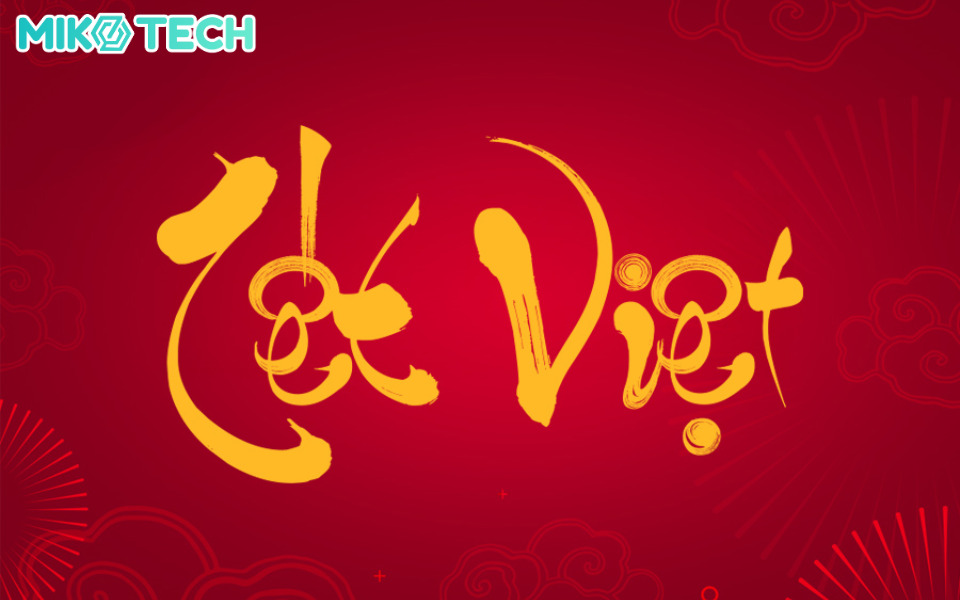
15+ Font Chữ Tết Chúc Mừng Năm Mới Ấn Tượng Và Độc Đáo
Chọn font chữ Tết phù hợp không chỉ giúp bạn tạo điểm nhấn mà còn mang lại cảm giác ấm áp, vui tươi cho các thiết kế dịp năm mới. Hiện nay, có rất nhiều font Tết đẹp với nhiều phong cách khác nhau từ thư pháp cổ điển cho đến hiện đại. Trong bài viết này, Miko Tech sẽ chia sẻ bộ sưu tập font chữ Tết đẹp mắt, giúp bạn thổi hồn xuân vào mỗi thiết kế.
Font chữ Tết là gì?
Font chữ Tết là các kiểu chữ được thiết kế để phù hợp với không khí và tinh thần của Tết Nguyên Đán, mang đậm phong cách lễ hội truyền thống của người Việt Nam.
Font chữ Tết đẹp
Font chữ đẹp sẽ giúp nâng tầm thiết kế của bạn
Font chữ Tết mang đậm dấu ấn văn hóa Phương Đông gợi nhớ về những hình ảnh quen thuộc trong mùa Tết. Các font Tết thường được lấy cảm hứng từ thư pháp hoặc nét viết tay mềm mại, uyển chuyển. Những font chữ Tết được sử dụng trong các thiết kế liên quan đến Tết như bao lì xì, thiệp chúc mừng, banner, poster, hoặc các sản phẩm trang trí vào dịp Tết.
Tổng hợp 15+ font chữ Tết đẹp trong thiết kế
Khi thiết kế với chủ đề Tết, việc chọn font chữ phù hợp là một thử thách thú vị. Làm sao để tìm được font chữ Tết không chỉ mang đậm nét văn hóa truyền thống mà còn thể hiện được màu sắc riêng của nhà thiết kế hoặc thương hiệu? Cùng xem qua những font chữ chúc mừng năm mới đẹp, độc đáo ngay sau đây!
1. Font chữ Tết TH Culture
TH Culture là một font Tết đẹp cho những thiết kế năm mới mang đậm phong cách trẻ trung nhưng vẫn dễ nhìn. Với kiểu chữ to bản kết hợp những đường nét uốn lượn mềm mại, TH Culture không chỉ mang vẻ đẹp hoài cổ mà còn tỏa lên sự thanh lịch và tinh tế. TH Culture sẽ là font chữ lý tưởng để sử dụng làm font chữ chúc mừng năm mới cho các thiết kế bao bì, social post, banner của các thương hiệu bánh ngọt hoặc hoạt động trong lĩnh vực F&B.
Font chu TH Culture xua hoai co
Font chữ tết đẹp TH Culture xưa hoài cổ
2. Font Thư Pháp Đức Thủy
Thư Pháp Đức Thủy là một font chữ tết thư pháp vô cùng ấn tượng và độc đáo. Với các nét chữ sắc sảo, vừa cứng rắn vừa uyển chuyển, Thư Pháp Đức Thủy là một font chữ Tết đậm đà bản sắc dân tộc và mang đậm tinh thần lễ hội. Ngoài ra, với khả năng hiển thị tốt trên nhiều chất liệu, font chữ Tết này rất hoàn hảo với các banner in câu đối, phong bì lì xì hay thậm chí cho các quảng cáo game kiếm hiệp sự kiện Tết nguyên đán.
Font Chữ Tết Thư Pháp Đức Thủy
Font chữ Tết Thư Pháp Đức Thủy
3. Font Tết Thư Pháp Đại Tự
Thư Pháp Đại Tự là một font chữ Tết thư pháp tuyệt vời cho những thiết kế mang đậm bản sắc văn hóa truyền thống Việt Nam. Các ký tự được dựa theo chữ viết thư pháp và nét bút đậm nhạt như khắc họa được lực tay của người cầm bút. Font Thư pháp Đại Tự có thể được sử dụng trong các sản phẩm như thiệp chúc Tết, câu đối, bao bì, hay các ấn phẩm đặc biệt trong Tết, mang đến sự trang trọng và đậm đà bản sắc dân tộc.
Font chu Tet dep Thu Phap Dai Tu 1
Font chữ Tết thư pháp Đại Tự
4. Font Tết Fantomen Việt hóa
Font Fantomen Việt hóa là một font chữ Tết đầy hoài cổ, gợi nhớ đến những nét đẹp xưa cũ của đất nước giai đoạn sau Giải phóng miền Nam. Lấy cảm hứng từ những bảng hiệu cũ trên đường phố ngày xưa, font chữ gốc của tác giả Bartek Nowak đã được Việt hóa để tái hiện nguyên vẹn giá trị văn hóa Việt Nam. Ngày nay, font chữ Fantomen Việt hóa có thể được dùng để thiết kế biển hiệu, bìa sách, bìa tạp chí, ấn phẩm truyền thông hoặc bao bì sản phẩm.
Font chữ tết Fantomen Việt hóa
Font Tết Fantomen Việt hóa cổ điển
5. Font chữ Christmas Carol
Christmas Carol là font chữ giáng sinh có nét chữ mềm mại, uốn lượn nhẹ nhàng và mang phong cách thư thái, lãng mạn. Khi được Việt hóa, font chữ này được sử dụng nhiều trong các ấn phẩm dịp lễ, kể cả dịp Tết, banner quảng cáo hoặc card cám ơn khi đóng gói sản phẩm.
font chữ christmas carol
Font chữ Christmas Carol có thể dùng được cho nhiều dịp lễ
6. Font chữ Tết Medino
Medino Serif là một kiểu chữ hiện đại với các đường nét gọn gàng, đường cong ấn tượng và mang đến một cảm giác sang trọng và đẳng cấp. Mặc dù được thiết kế để phù hợp cho tiêu đề, logo và bao bì sản phẩm nhưng Medino Serif hoàn toàn có thể trở thành lựa chọn tuyệt vời cho các thiết kế dịp Tết.
Medino Serif với các nét đầu, nét đuôi sang chảnh sẽ giúp chữ viết được đẹp mắt hơn nhưng vẫn đảm bảo mức độ dễ đọc. Font chữ Tết này có thể kết hợp tốt với các thiết kế tối giản và sang trọng, giúp nhãn hiệu và bao bì sản phẩm có vẻ đẹp tinh tế và độc đáo.
Font chu chuc mung nam moi Medino 1 1
Font chữ chúc mừng năm mới Medino
7. Font chữ cho Tết Sverige Script
Sverige Script là một kiểu chữ thanh thoát và điệu đà, mang lại vẻ đẹp mềm mại và uyển chuyển cho mọi thiết kế. Font chữ Tết Sverige Script có đường nét mảnh, đầy lãng mạn và hoàn hảo cho những dự án thiết kế dịp Tết. Hiện nay, font Tết đẹp Sverige Script đã được Việt hóa, do đó bạn có thể tải xuống để làm nổi bật các thông điệp xuân.
Font tet dep Sverige Script 1
Font Tết đẹp Sverige Script
8. Font Tết Classique Saigon Typeface
Font Classique Saigon Typeface là font chữ chúc mừng năm mới mang đậm dấu ấn hoài cổ được sáng tạo bởi tác giả Mạnh Nguyễn. Lấy cảm hứng từ những bảng hiệu cũ ở Sài Gòn giai đoạn Pháp thuộc, tác giả đã sáng tạo nên font chữ ấn tượng và phù hợp với những ấn phẩm hoặc thiết kế theo phong cách retro.
Xem thêm: 17+ Font Chữ Có Chân Đẹp Mắt, Thanh Lịch
font chữ cho tết Classique Saigon Typeface
Font chữ Tết Classique Saigon Typeface hoài cổ
9. Font Tết đẹp Rocky Việt hóa
Nếu bạn đang tìm kiếm một font chữ Tết độc đáo và phá cách thì Rocky Việt hóa sẽ là một sự lựa chọn đáng cân nhắc. Sự độc đáo của font chữ này nằm ở những nét cong có độ nghiêng lạ mắt chắc chắc sẽ tạo ấn tượng mạnh cho người xem ngay từ cái nhìn đầu tiên.
font chữ cho tết Rocky Việt hóa
Font chữ cho Tết Rocky Việt hóa
10. Font Tết UTM Spring
UTM Spring với những đường nét uyển chuyển và mềm mại mang đến một vẻ đẹp cổ điển đầy lôi cuốn. Font chữ cho tết này là lựa chọn lý tưởng để truyền tải không khí Tết, từ thiệp chúc mừng, bao lì xì đến lịch Xuân, mang lại sự ấm áp và gần gũi cho các sản phẩm trong dịp lễ hội. Với vẻ đẹp thanh thoát, font Tết UTM Spring sẽ giúp làm nổi bật các thông điệp chúc Tết và các thiết kế ngày xuân.
font chữ chúc mừng năm mới đẹp
Font UTM Spring với nét đẹp nhẹ nhàng
11. Font chữ Tết Azuki
Font Azuki Việt Hóa là font chữ Tết đầy sức hút hiện đại với đường nét dày, bo góc mềm mại như nét bút lông. Font chữ Tết Azuki Việt hóa được bổ sung đầy đủ dấu tiếng Việt, giúp bạn dễ dàng sử dụng cho các thiết kế thiệp chúc mừng năm mới, bao lì xì hoặc hình trang trí năm mới. Mang phong cách năng động, trẻ trung, Azuki sẽ thổi một làn gió mới cho tác phẩm đầu năm của bạn.
Font chu tet Viet hoa UTM Azuki 1
Font chữ tết Việt hóa UTM Azuki
12. Font UTM Ông Đồ Già
Font Ông Đồ Già Việt Hóa là font chữ Tết lấy cảm hứng từ thư pháp, vừa mang màu sắc truyền thống lại vừa dễ đọc và kết hợp tốt với các thiết kế hiện đạivà tính linh hoạt hiện đại. Font chữ Ông Đồ Già với phong cách thư pháp độc đáo không chỉ giúp kết nối với truyền thống mà còn mang đến sự sang trọng và ý nghĩa cho các dự án thiết kế mùa xuân, tôn vinh vẻ đẹp văn hóa Việt.
font chữ tết thư pháp
Font chữ chúc mừng năm mới UTM Ông Đồ Già quen thuộc
13. Font FZ thư pháp Bút Bi
Tiếp tục là một font chữ tết thư pháp, Font FZ Thư Pháp Bút Bi với đường nét mảnh nhưng vẫn giữ được phong cách chữ thư pháp mang lại cảm giác vừa quen thuộc vừa mới lạ. Vì nét chữ có độ mảnh, font Tết này sẽ không phù hợp để dùng làm tiêu đề của thiết kế. Tuy nhiên, bạn có thể sử dụng FZ Thư Pháp Bút Bi để bổ trợ cho các font chữ thư pháp có độ dày nét cao hơn.
Font FZ thu phap But Bi cho ngay tet 1
Font FZ thư pháp Bút Bi cho ngày tết
14. Font Tết đẹp MTD Blaze Glory
MTD Blaze Glory là một font chữ Tết có sự kết hợp giữa vẻ đẹp cổ xưa và hiện đại. Với những đường nét mạnh mẽ và góc cạnh, font chữ này tạo ra sự cuốn hút khó cưỡng, đồng thời mang đến bản sắc văn hóa đặc biệt. Gợi nhớ đến không khí Tết xưa cũ, font Tết MTD Blaze Glory là sự lựa chọn lý tưởng cho các thiết kế hiện đại nhưng vẫn chất chứa linh hồn dân tộc.
Khám phá thêm: Tải 50+ Font Chữ Cho Photoshop Đẹp, Đầy Đủ
font tết đẹp MTD Blaze Glory
Font chữ Tết độc đáo, ấn tượng MTD Blaze Glory
15. Font chữ TH Lichsu 1
Font chữ Tết TH Lichsu 1 là một font chữ đặc trưng với các đường nét vững chãi, vuông vức gợi lên sắc thái uy nghi, mạnh mẽ. Font chữ này gợi chúng ta nhớ đến những công trình kiến trúc thời phong kiến với các trụ thẳng đứng và nét vát lạ mắt. Nếu bạn đang tìm kiếm một font chữ chúc mừng năm mới có phong thái mạnh mẽ thì TH Lichsu 1 sẽ là một font chữ đáng để cân nhắc.
Font chuc mung nam moi TH Lichsu 1
Font chúc mừng năm mới TH Lichsu 1
16. Font chữ HC Pacifico
HC Pacifico là font chữ chúc mừng năm mới mang đậm phong cách hoài cổ với những nét bo tròn và dày dặn, tạo cảm giác thân thiện và vô cùng ấm áp. Với vẻ ngoài thanh thoát và dễ chịu, font chữ Tết HC Pacifico sẽ mang lại cảm giác ấm áp, thân thuộc cho các sản phẩm liên quan đến Tết dù là thiệp mời, bao lì xì, poster hay bất kỳ ấn phẩm nào.
Font chu tet hoai co TH Pacifico 1
Font chữ hoài cổ TH Pacifico
17. Font chữ Tết Angrela Display
Angrela Display thường được đánh giá là có nét đẹp hiện đại, trẻ trung với những đường nét thanh mảnh và tinh tế. Font Tết này mang đến cảm giác tươi mới, năng động và rất phù hợp với các thiết kế mang hơi hướng trẻ trung, hiện đại. Nếu bạn muốn thiết kế Tết của mình mang phong cách tao nhã, hiện đại thì đây sẽ là font chữ đáng để thử nhé.
Font chữ cho Tết Angrela Display
Tổng kết